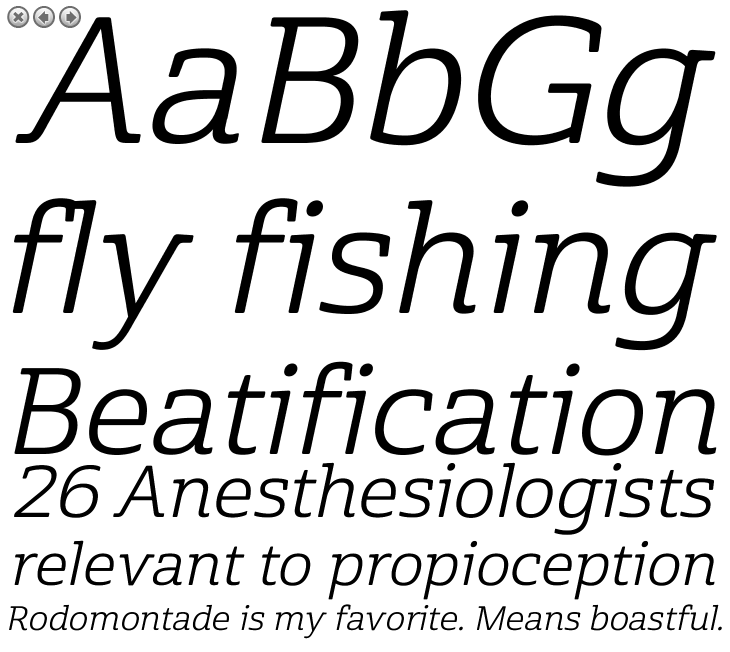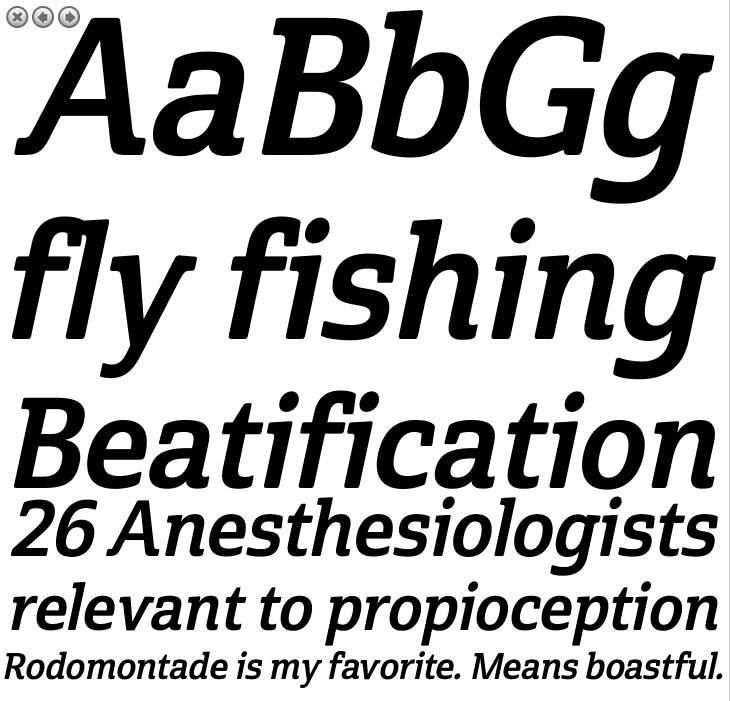
Suche Windows Sytemfont als Alternative zur Cabrito Semi
ich verwende für einen Kunden die „Cabrito Semi“ im Schnitt „Italic“. Diese läuft sowohl auf Mac als auch auf Windows und wird auch online bereits eingesetzt.  Nun wünscht sich der Kunde eine Alternative, ein Windows Systemfont, der der CI Schrift, eben besagter Cabrito Semi nahe kommt, da sie diese als Ergänzung gerne einsetzen möchten. Daher meine Frage …
- Wie heißt die Schrift auf dieser Plattform?
- Und ist diese eine Windows Systemfont?
- Weiß jemand eine Windows Systemfont Alternative zur Cabrito Semi?
Schau dir mal die Kursiven der Cambria und Georgia an (beides Windows-Systemschriften). Die sind immer noch meilenweit von der Cabrito entfernt, sind aber wenigstens nicht serifenlos.
Nun wünscht sich der Kunde eine Alternative, ein Windows Systemfont, der der CI Schrift, eben besagter Cabrito Semi nahe kommt, da sie diese als Ergänzung gerne einsetzen möchten.
Kannst du mal erklären, weshalb sich der Kunde als Alternative einen Systemfont wünscht? Und wofür genau?
Üblicherweise für Anwendungen, in denen die Hausschrift nicht eingebunden werden kann oder darf. Powerpoint-Präsentationen beispielsweise …
Dafür müsste es aber kein Systemfont sein, oder? Es gibt mittlerweile doch auch sehr gut ausgebaute freie Fonts w. z. B. die Adobe Source Sans. Die ist unter Windows recht gut am Bildschirm lesbar.